Рукописные «л», «п» и «т»: как разделить дуговые формы
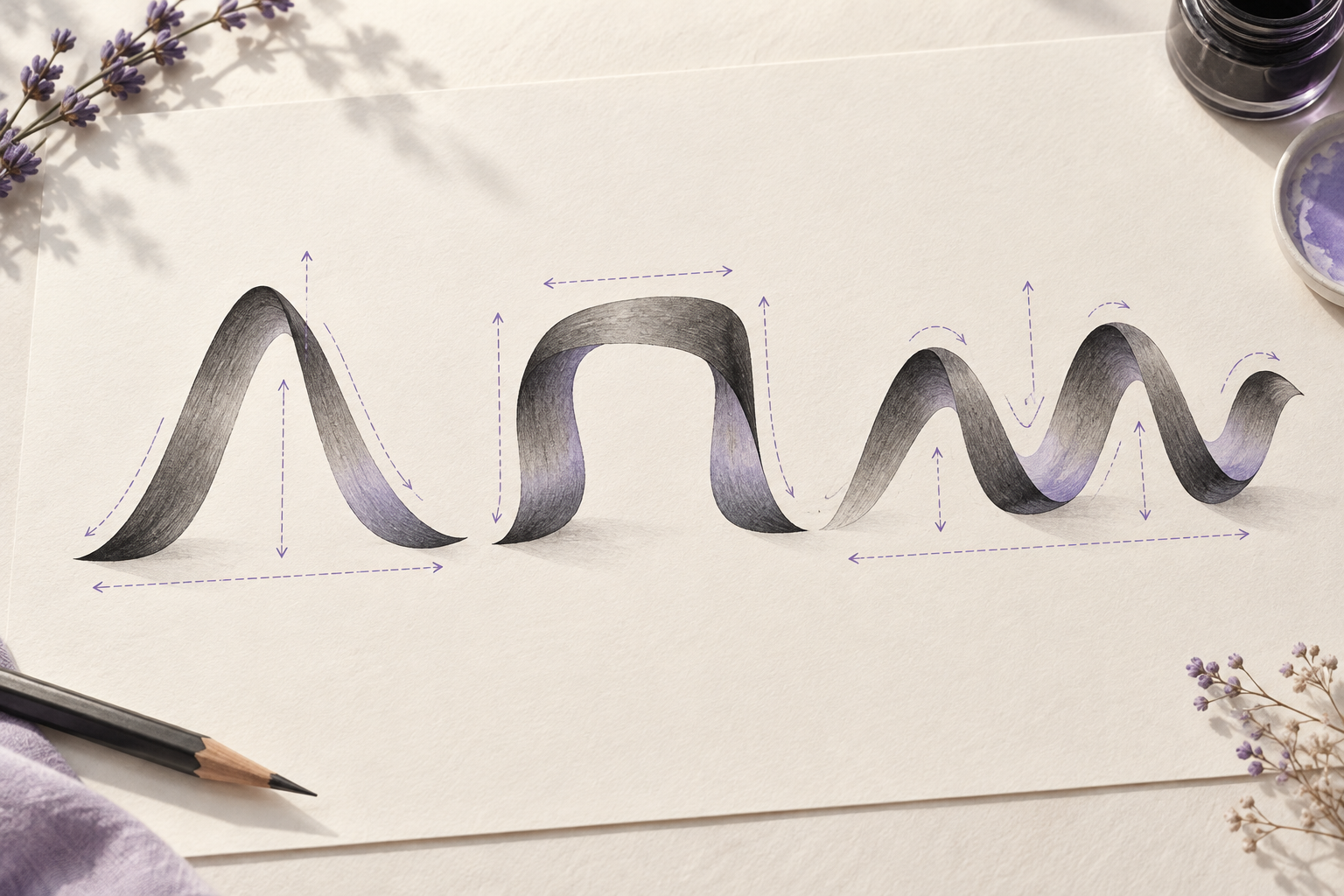
В рукописном шрифте строчные «л», «п» и «т» могут сблизиться, если их построить из одинаковых дуг и одинаково соединить с соседями. Различимость возникает не из одного «правильного» начертания, а из набора устойчивых признаков: числа вершин, ширины, высоты плеча, направления штрихов и способа входа и выхода. Ниже — рабочий способ проверить эту группу и внести небольшие, контролируемые правки.
Почему эти формы стоит сравнивать вместе
У букв «л», «п» и «т» нет универсального набора контуров, который обязан повторять каждый авторский шрифт. Рукописный стиль допускает разные углы, петли, наклоны и способы соединения. Поэтому проверять нужно не соответствие образцу из чужого алфавита, а то, остаются ли ваши формы разными внутри собственной системы.
Риск возникает, когда три буквы собираются из повторяющихся подъёмов и спусков. У «л» обычно важны две стороны и вершина, у «п» — стойки и верхнее соединение, у «т» — более сложный ритм, который в рукописной подаче может напоминать несколько соседних дуг. Если убрать небольшой изгиб, опустить верхнюю точку или вытянуть соединительный штрих, различительный признак исчезает. Слово иногда удаётся прочитать по смыслу, но при этом сама форма остаётся неясной.
Это не означает, что читатель обязательно перепутает именно эти буквы. В одном почерке они уже заметно отличаются шириной и углом, а в другом все выглядят как одинаковые арки. Сравнение этой группы полезно как проверка: оно показывает, не превратился ли повторяющийся элемент алфавита в однообразный рисунок.
Какие признаки разделяют «л», «п» и «т»
Начните с общего силуэта. Поставьте три знака рядом в одинаковом кегле и на одной базовой линии. Сначала смотрите не на внутренние детали, а на ритм верхних точек и нижних опор: где форма поднимается, где меняет направление, сколько раз глаз должен пересечь вершину. Если контуры читаются как три одинаковые арки, сравнение в словах пока рано — сначала найдите разницу в самих глифах.
Вершины и число направлений
У «л» силуэт часто держится на одном подъёме и одном спуске: две наклонные стороны сходятся или почти сходятся, а затем расходятся к основанию. У «п» читатель должен увидеть две стойки и перемычку между ними; верхнее соединение создаёт закрытый или почти закрытый просвет. У рукописной «т» рисунок может быть более волнистым, но её нельзя сводить к неразборчивому набору одинаковых горбиков.
Не обязательно считать каждый штрих буквально. Проверяйте, какой путь проходит взгляд: сколько раз линия меняет направление и где находится верхняя точка. Если «т» и «п» различаются только одним коротким участком, который исчезает при уменьшении, а «л» отличается только наклоном, при обычном чтении эти сигналы могут быть слишком слабыми.
Ширина, наклон и просвет
Сравните пропорции при одинаковой высоте. Разницу можно выразить через ширину глифа, угол боковых штрихов или форму внутреннего просвета. «П» не обязана быть шире «л», а «т» не обязана иметь фиксированное число дуг: это решения дизайна. Важно, чтобы относительная ширина не оказалась случайной и не стирала конструкцию. Очень узкая «п» может походить на «л», а слишком широкая «л» — на две стойки с перемычкой.
Проверьте и наклон. Если все три формы наклонены в одну сторону одинаково, наклон перестаёт помогать распознаванию. Если же отдельная буква наклонена иначе, она может выглядеть чужеродно. Ищите умеренный контраст внутри общей манеры письма: например, яснее различите направление боковых штрихов или сделайте просвет у одной формы заметно открытым.
Входной и выходной штрих
В связном начертании контур буквы продолжается к соседнему знаку. Один и тот же глиф поэтому может выглядеть по-разному в начале, середине и конце слова. Входной штрих способен закрыть просвет «п», а выходной — добавить лишнюю вершину рядом с «л». Проверяйте отдельно форму основы и её соединения: иначе можно начать менять саму букву, хотя проблема находится в коротком переходе.
Удобно временно показать букву без соседнего соединения, а рядом — две реальные связки. Сравните, где заканчивается основная конструкция и где начинается переход. Если читателю трудно определить число арок, испытайте более ясный выход: измените точку отрыва, направление или высоту соединения, сохраняя общий характер линии.
Порядок проверки на практике
Шаг 1. Соберите нейтральную строку
Наберите или нарисуйте одинаковую последовательность из трёх букв, например «ллл», «ппп» и «ттт», а затем смешанную строку «лптплт». Повтор помогает увидеть ширину и ритм, но не заменяет чтение слов. Сделайте образцы одного размера и не подписывайте буквы возле каждого знака: подпись заранее подсказывает ответ.
Шаг 2. Зафиксируйте ожидаемый признак
Для каждой буквы сформулируйте одну проверяемую подсказку: «у этой формы заметна вершина», «у этой — две стойки и перемычка», «у этой — иной ритм подъёмов». Если объяснение получается только через название буквы или длинный рассказ о том, как она рисовалась, визуальный признак пока неочевиден. Запишите причину, чтобы можно было понять, что изменилось после правки.
Шаг 3. Проверьте несколько окружений
Поместите формы в слова с разными соседями: например, сравните «пол», «плот», «толк» и «тополь». Подберите также сочетания, где буква стоит у края слова и внутри него. Смысл знакомого слова помогает чтению, поэтому добавьте короткую строку без очевидной подсказки — например, нейтральную последовательность слогов. Она нужна не для оценки языка, а чтобы увидеть, насколько форма сама подсказывает букву.
Если неоднозначность проявилась только в одном сочетании, не меняйте все три знака сразу. Увеличьте образец и выясните, скрывает ли соседняя буква вершину, касается ли выходной штрих просвета, меняется ли межбуквенное расстояние. Локальная причина требует локальной правки.
Шаг 4. Изменяйте одну переменную за проход
Попробуйте отдельно скорректировать угол бокового штриха, ширину, высоту вершины, открытость просвета или место соединения. Не меняйте одновременно весь силуэт и наклон: сравнение версий перестанет показывать, какое действие помогло. Сохраните исходный рисунок, сделайте рядом два варианта и попросите читателя назвать буквы без предварительного объяснения.
Для нейтральной проверки меняйте порядок вариантов и не спрашивайте «видна ли разница». Лучше показать строку и попросить прочитать её вслух или переписать. Так вы узнаете не только, замечает ли человек изменение, но и смог ли он использовать его при чтении.
Шаг 5. Вернитесь к размеру и материалу использования
Крупный образец показывает устройство штриха, но мелкий размер может скрыть маленький угол или просвет. Проверьте шрифт в том размере и на том носителе, для которых он создаётся: на экране, в печатном тексте или на короткой надписи. Если контраст исчезает, усиливайте только тот признак, который нужен для распознавания, а не утолщайте или раздвигайте весь алфавит автоматически.
Ошибки при работе с дуговыми буквами
Считать одинаковое число петель гарантией сходства. Читатель видит не только петли, но и их ширину, наклон, вершины и переходы. Два одинаковых по счёту изгиба могут читаться по-разному, если их внешний контур и соединения различаются.
Делать букву нарочито угловатой. Резкий угол действительно может отделить один глиф от мягкого соседнего, но он способен выбиться из общего почерка. Сначала проверьте небольшой сдвиг вершины или ширины; более заметное изменение оставьте для случая, когда мягкой корректировки недостаточно.
Проверять только изолированные знаки. В одиночном глифе видны контуры, но не то, что случится с входом и выходом в слове. Используйте и карточку с отдельными буквами, и строку с реальными соседями.
Полагаться на подсказку из слова. Читатель может догадаться по знакомому слову, хотя форма остаётся двусмысленной. Поэтому сравнивайте узнаваемые примеры с нейтральными сочетаниями и просите прочитать их без подсказки.
Править всю группу сразу. Если у «л», «п» и «т» одновременно изменить пропорции, ритм и соединения, будет трудно сохранить исходный стиль и найти источник улучшения. Уточняйте один отличительный признак за раз, затем проверяйте все три формы повторно.
Чек-лист перед выпуском
- Сравните «л», «п» и «т» в одинаковом масштабе и на одной базовой линии.
- Назовите для каждой буквы один видимый признак, который отличает её от соседних форм.
- Проверьте вершины, ширину, наклон, просвет и выходной штрих отдельно.
- Поставьте буквы в начало, середину и конец разных слов.
- Добавьте нейтральное сочетание, где смысл не подсказывает прочтение.
- Попросите человека без предварительного объяснения прочитать строку.
- Вносите за один проход одну правку и сохраняйте исходный вариант для сравнения.
- Повторите чтение в реальном размере и на предполагаемом носителе.
Нужно ли всем рукописным шрифтам менять форму «л», «п» и «т»?
Нет. Если в конкретном шрифте формы уверенно различаются, изменять их не требуется. Эта проверка нужна, когда одинаковые дуги, ширина или соединения делают буквы похожими именно в вашем рисунке.
Какая из трёх букв должна быть самой широкой?
Универсального правила нет. Ширину выбирают внутри пропорций гарнитуры и проверяют рядом с другими буквами. Важен не отдельный норматив, а то, чтобы ширина и просвет помогали отличить конструкцию от соседних форм.
Можно ли соединять эти буквы без отрыва пера?
Можно, если соединение не закрывает просвет и не добавляет к силуэту лишнюю вершину. Проверяйте вход и выход в нескольких сочетаниях, поскольку переход, удачный с одной стороны, может затруднить чтение рядом с другим знаком.
Достаточно ли проверить «лпт» крупно на листе?
Нет. Крупный образец помогает рассмотреть конструкцию, а обычный размер показывает, остаётся ли различие заметным при чтении. Проверяйте обе ситуации и используйте слова с разными соседними буквами.
Что делать, если читатель ошибся только в одном слове?
Сначала выясните, не возникла ли проблема из-за соседнего соединения или интервала. Если изолированная буква и другие слова читаются правильно, поправьте локальный переход. Если одну и ту же букву путают в разных сочетаниях, пересмотрите её основной контур.
Как понять, что различие уже достаточно заметно?
Дайте человеку, не знакомому с макетом, прочитать несколько неподписанных примеров без подсказки о проблемной паре. Если буквы читаются без регулярных замен, а правки не нарушили единый характер шрифта, дальнейшее усиление контраста может быть не нужно.
Проверка «л», «п» и «т» как группы помогает увидеть, где повторяющийся дуговой ритм начинает скрывать устройство отдельных букв. Разделяйте формы по вершинам, пропорциям и соединениям, меняйте один признак за раз и проверяйте результат в словах и обычном размере. Когда набор готов, можно создать свой рукописный шрифт в Fontgenerator и испытать его на собственном тексте.